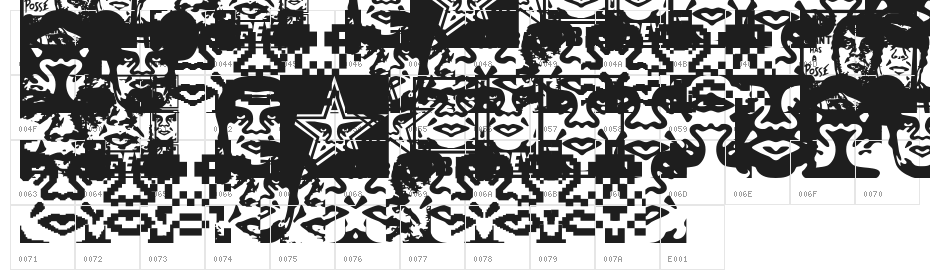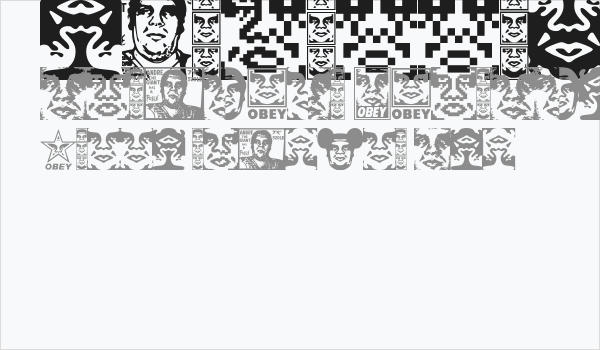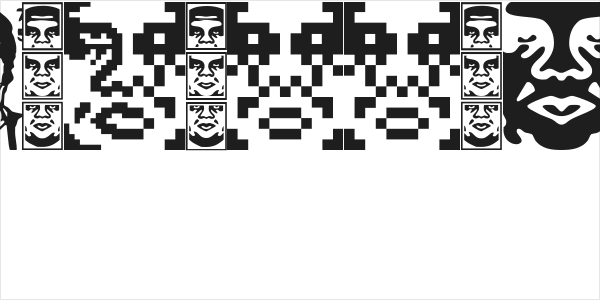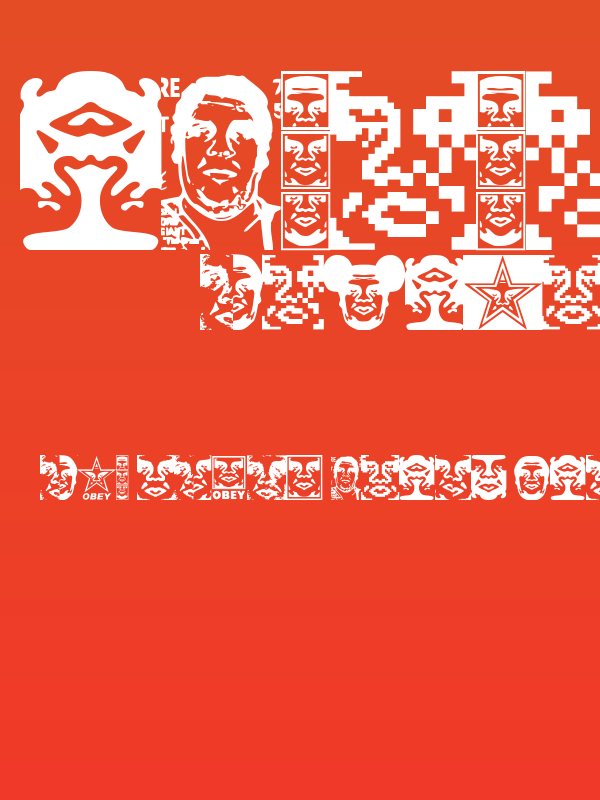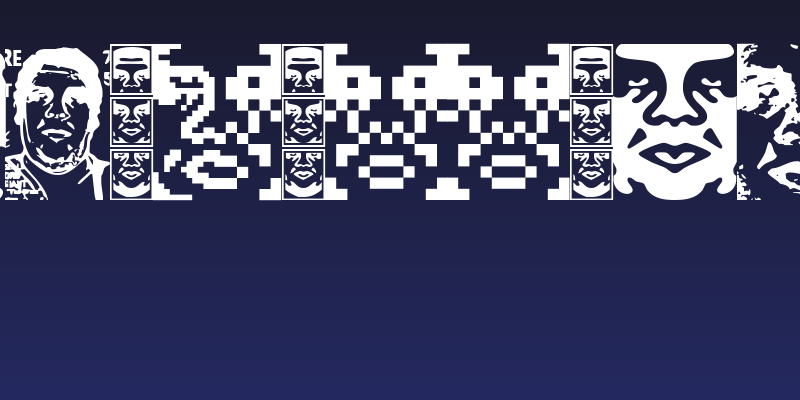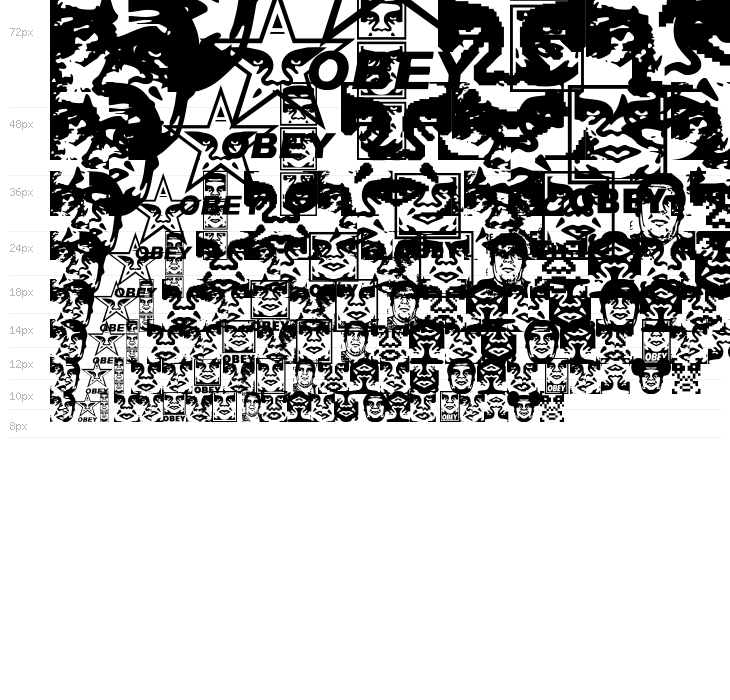
ObeyEssence Font
| Stile generale | Decorative, Urban, Pop Art |
| Caso d'uso | Logos, Headlines, Posters, Artistic projects |
| Progetti proposti | Posters, album covers, urban art projects, branding for streetwear, event flyers, and creative campaigns. |